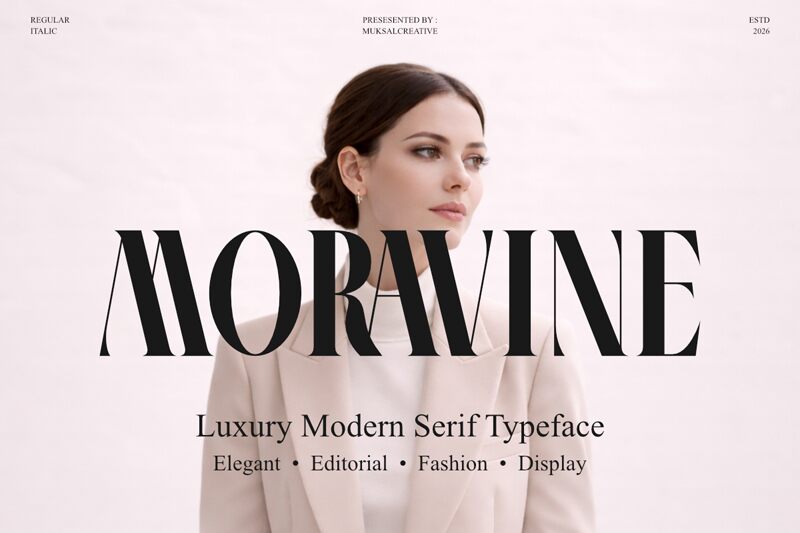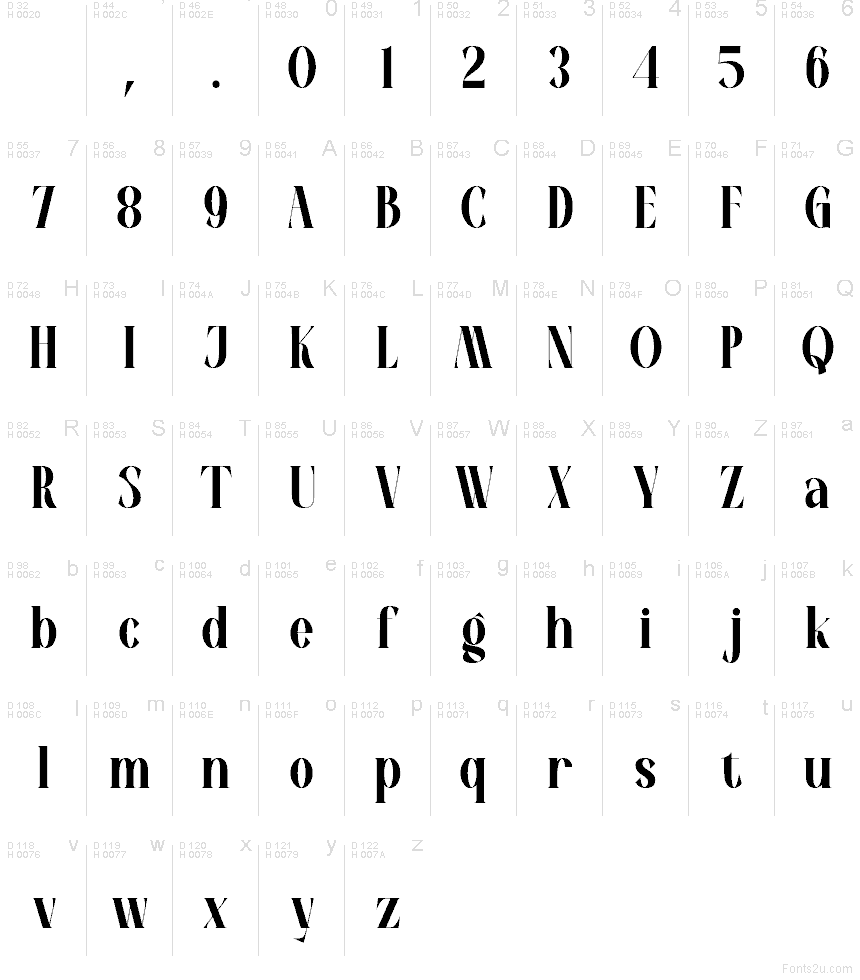
Moravine Regular
Moravine, bezplatné písmo s vysokým kontrastom od Muksal Creative, definuje vysoká a zúžená silueta, v ktorej sa široké oválne tvary stretávajú s veľmi jemnými ťahmi a ostrými uhlovými zakončeniami. Tento kontrast dodáva písmenám elegantný, vycibrený rytmus, takže písmo pôsobí sofistikovane bez toho, aby bolo prezdobené.
Je ideálne pre módne editoriály, obaly kozmetiky, branding butikov, pozvánky a menu luxusných kaviarní, kde trocha kontrastu postačí na dokonalý štýl. Najlepšie vynikne v krátkych nadpisoch a logách, pretože štíhle spoje a tvarované krivky dodávajú každému slovu čistý a elegantný obrys.